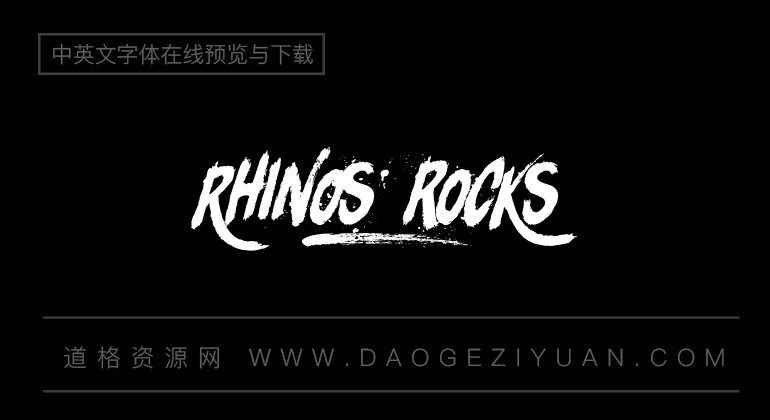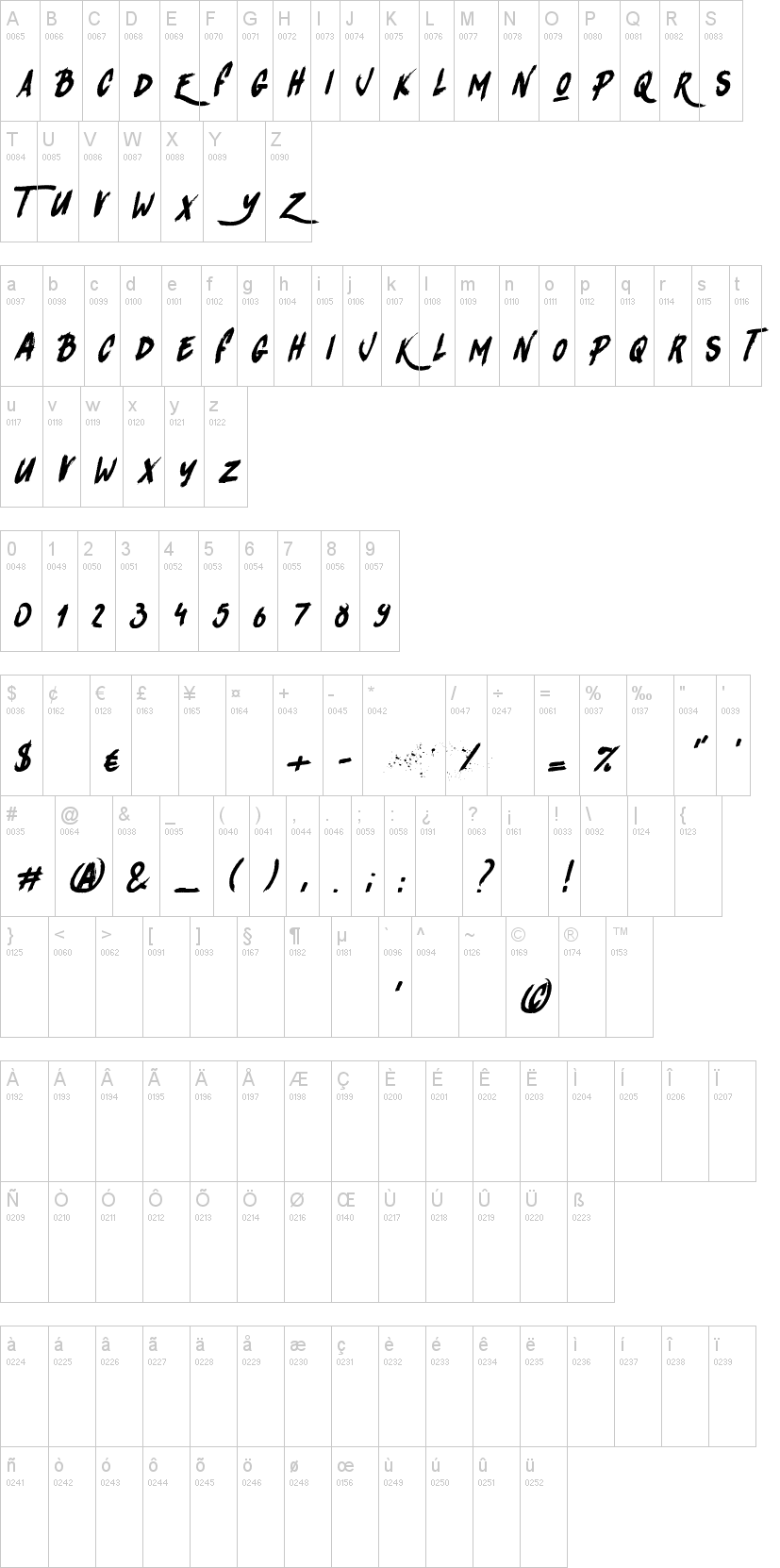
Rhinos rocks 是一款字体,它有着独特的设计,可以满足不同的设计需求。它具有简洁的外观,可以提供清晰的文本,并且可以更好地表达您的设计意图。它还有一种混合字体,可以提供更多的设计可能性。内容介绍
Rhinos rocks是一款非常不错的手写艺术字体,具有很好的视觉感,适合于文化类的宣传设计、商业类品牌的广告和产品包装设计以及个性化文字排版等较多场景。